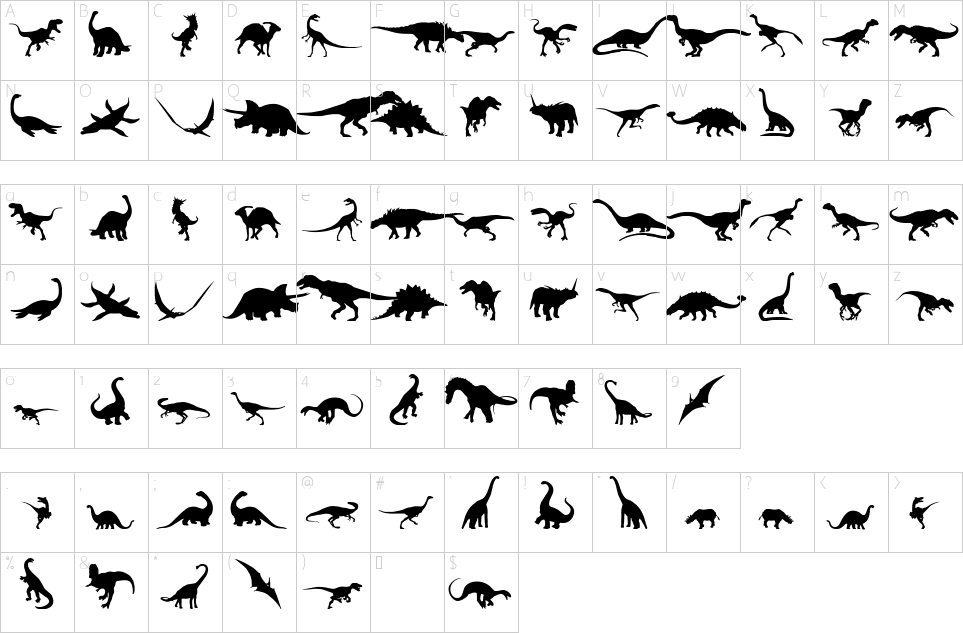
Aqui está uma descrição envolvente para a página de download da font ‘Dingosaurs Font’ no português do Brasil: Na árvore da linguagem digital, surge uma fonte que parece ter saído diretamente de um livro de fantasia: Dingosaurs. Este design único, criado pela incrível equipe de Iconian Fonts, traz à vida os dinossauros em cada palavra escrita. Não é apenas uma fonte; é uma experiência visual que mergulha o usuário no mundo imaginário dos dinossauros. Dingosaurs não apenas reúne toda a majestade dos maiores répteis terrestres, mas também incorpora sutilezas e detalhes que tornam cada linha de texto única. Seja para assinaturas profissionais ou escritos em livros infantis sobre fósseis, esta font apresenta um charme único que certamente vai ganhar o coração dos amantes do design gráfico. Com a Dingosaurs Font, você encontra uma maneira perfeita de dar vida aos livros e projetos, transformando simples textos em obras de arte. Seja uma estilizada ou mais retrô, esta font é um verdadeiro acréscomo para qualquer projeto que o usuário escolher.